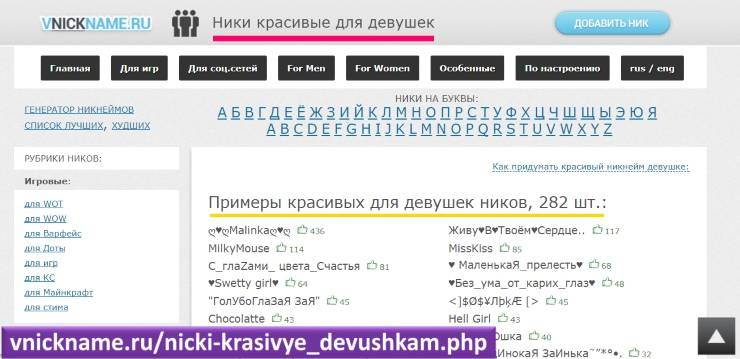
Генератор ников, поможет вам составить красивый ник для социальных сетей и игр. Например, для инстаграм, ютуб или САМП.
Наш генератор ников работает с базой данных слов английского и русского языка, у нас в запасе более 30тыс слов, благодаря такой базе мы перебираем каждое слово и генерируем для вас уникальный ник. Вы можете управлять процессом генерации, для этого выберите соответствующие настройки в генераторе.
Чтобы не запоминать понравившейся ник, отложите его в список избранного, после того как наберется полный список, выберите самый красивый ник и забирайте его.
Функция «первая буква»
Укажите в соответствующие поле первую букву с которой должен начинаться ваш ник.
Если быть точнее, вы можете указать даже первые две буквы, но тогда количество ников будет
уменьшаться.
Количество символов
Тут мы не стали вас ограничивать одним полем, вы можете указать генератору какой длины вам выводить никнейм. Если ник нужен определенной длины, заполните поля «от» и «до» одинаковыми значениями.
Специальные символы в нике
Вы можете использовать специальный символы для вставки их в свой ник, с любой стороны, как слева, так и справа.
Генератор выдает сразу несколько вариантов написания ника, понравившейся ник вы можете скопировать или добавить в избранное и продолжить подбирать свой ник.
Красивые шрифты для ника
Никнейм – отображение нашей индивидуальности. Он олицетворяет то, что для нас ценно, кем мы является и к чему стремимся. Он представляют нашу личность на различных сайтах при общении с другими пользователями. Кроме названия ника, не менее важно его визуальное оформление, яркий и привлекательный шрифт. Поиск красивого шрифта может занять какое-то время, ведь в сети представлены тысячи вариаций, многие из которых платные. Да и подчас непонятно, как их скачать и использовать. В данном материале мы расскажем, где взять красивые и оригинальные шрифты для ника онлайн, а также поясним, как установить их на ваш ПК.
Где можно найти красивые шрифты для никнейма
Все многообразие шрифтов, доступных в сети, можно условно разделить в соответствии с несколькими основными признаками. Это необходимость оплаты за пользование фильтром (платные и бесплатные аналоги), а также характер используемых символов (латиница, кириллица и другие).
В сети существуют множество сайтов, на которых вы можете просмотреть номенклатуру шрифтов, и скачать оригинальный фонт для ника. Самые продвинутые из таких сайтов предлагают набрать какое-либо слово на сайте и посмотреть, как оно будет выглядеть в том или ином варианте. Англоязычные сервисы плохо воспроизводят слова, набранные кириллическими буквами.
Давайте разберём несколько сервисов, на которых вы можете скачать красивые и необычные шрифты для своего никнейма онлайн.
Fonts-online.ru – объёмная база интересных шрифтов
На отечественном ресурсе fonts-online.ru расположена огромная база шрифтов, большинство из которых вы можете скачать абсолютно бесплатно. Для удобства работы они разбиты по различным категориям (представлены справа на сайте). После перехода на ресурс выберите справа подраздел какие именно шрифты вам нужны (например, латинские или кириллические).
Кириллические шрифты на fonts-online.ruПросмотрите перечень имеющихся на ресурсе вариантов и кликнете на понравившийся. Вы перейдёте на страницу шрифта, где потребуется набрать капчу, и кликнуть на «Скачать», после чего файл будет загружен на ваш ПК.
Введите капчу и нажмите на «Скачать» для загрузки шрифта на ПКMyfonts.com – галерея красивых фонтов для ников
Функционал ресурса позволяет просмотреть, как будет смотреться ваш ник с тем или иным шрифтомЕсли какой-либо результат вам понравится и он подходит для ника, вы можете кликнуть на данный шрифт и скачать его на ПК бесплатно (или приобрести за дополнительную плату в случае платной версии).
Также можно поступить другим образом:
- Навести курсор мышки на понравившийся вам ник в перечне выведенных вариантов написания шрифта.
- Кликнуть на нём правой клавишей мышки.
- Выбрать «Сохранить изображение как».
Xfont.ru – бесплатная база фильтров для текста
Сайт xfont.ru являет собой ещё одну базу различных бесплатных шрифтов, которые можно скачать на ваш ПК. Здесь представлены многие виды – классические, экзотические, рукописные, военные, плакатные, газетные и другие.
Предположим, вы хотите передать скорость работы своей группы поддержки. Ну, а как появляются вещи, когда они быстрые и быстрые? Часто они кажутся наклонными и расплывчатыми:
Так что выбирайте шрифт с наклонной ориентацией. Хотя вы можете выбрать шрифт с наклонным дизайном, в этом нет необходимости. Выделение курсивом вашего шрифта должно помочь.